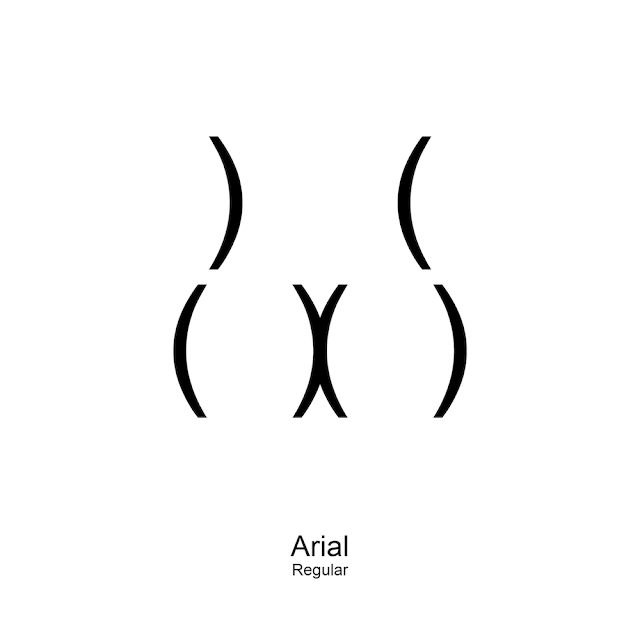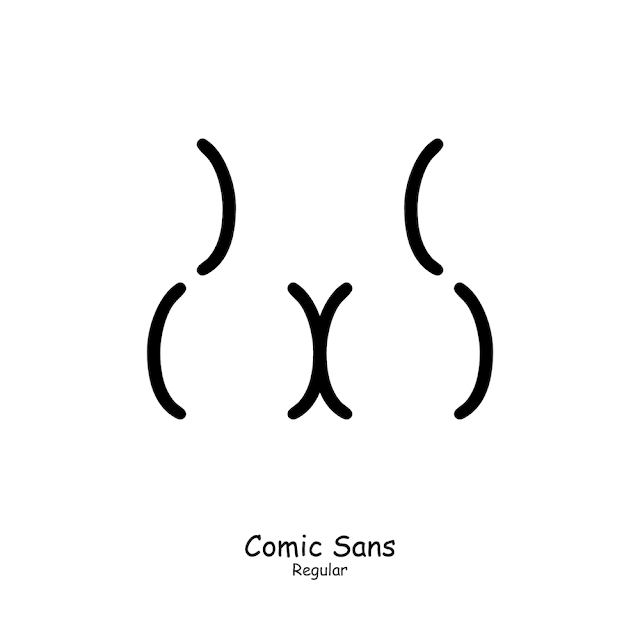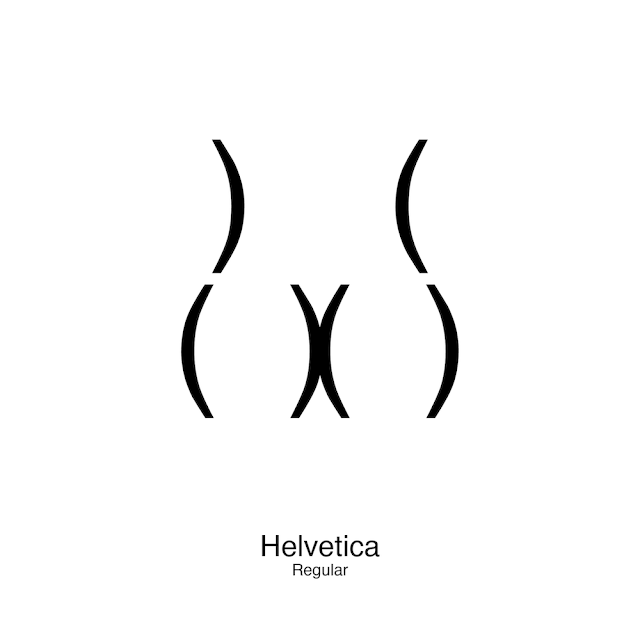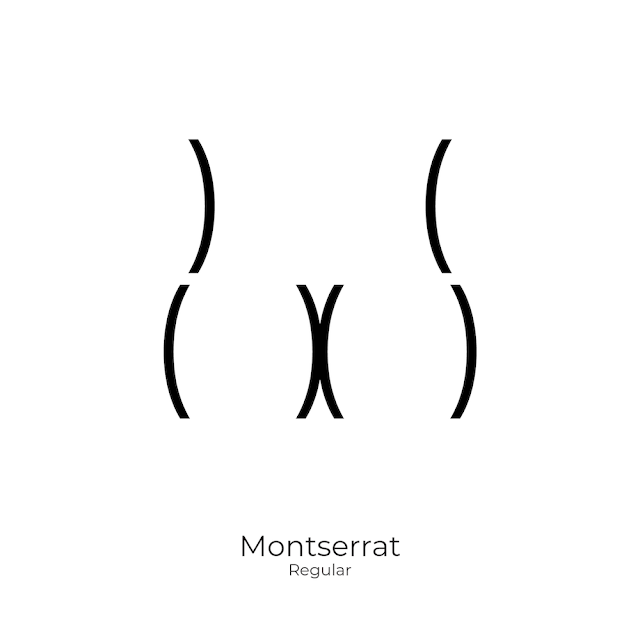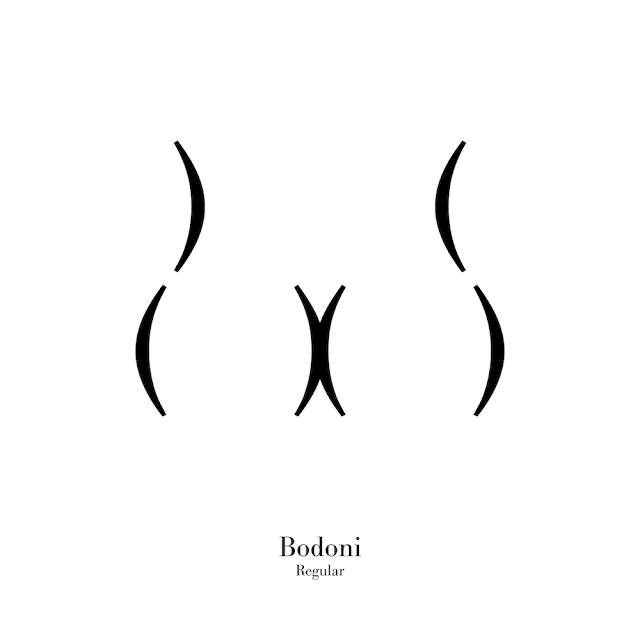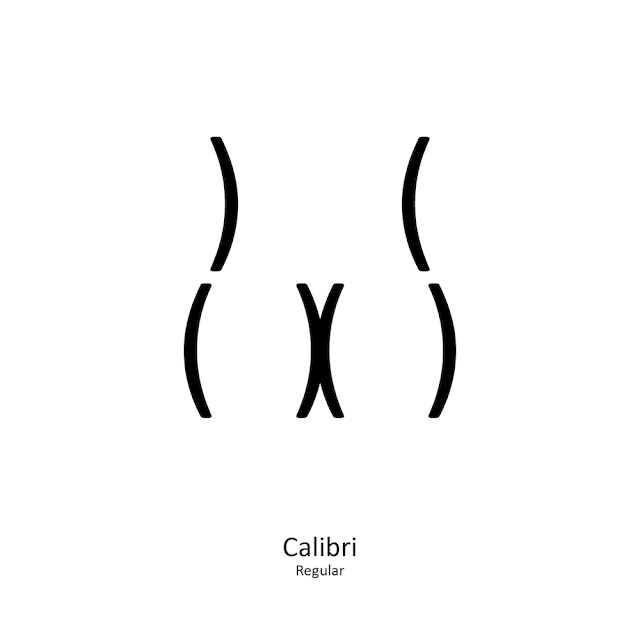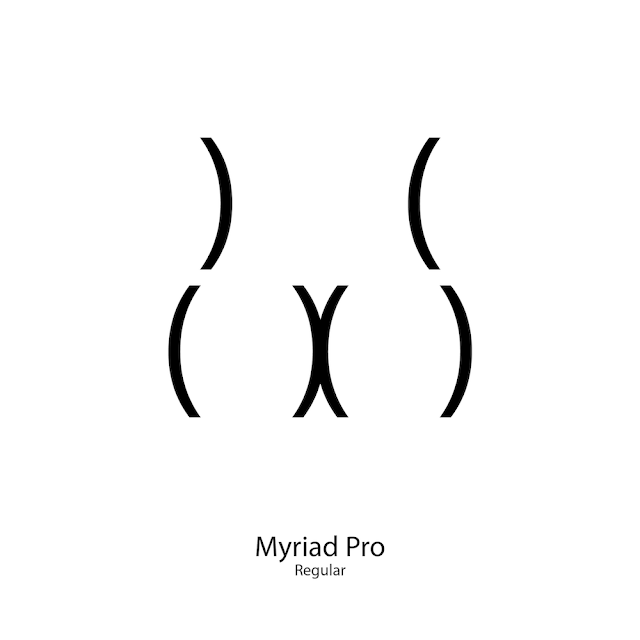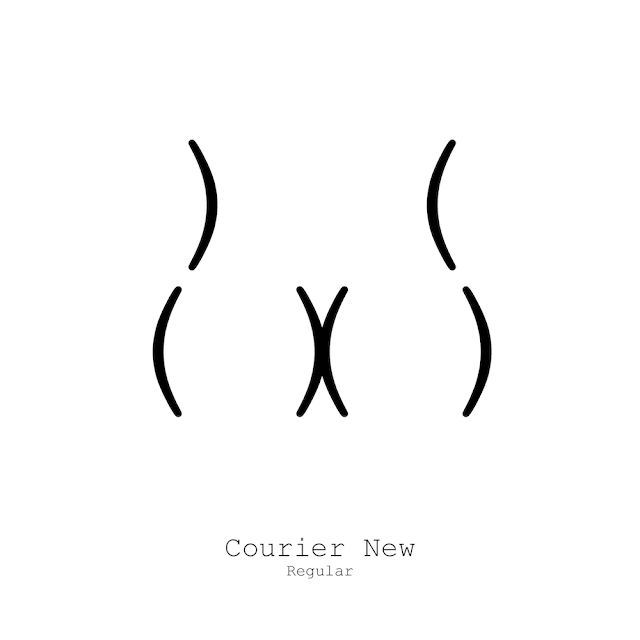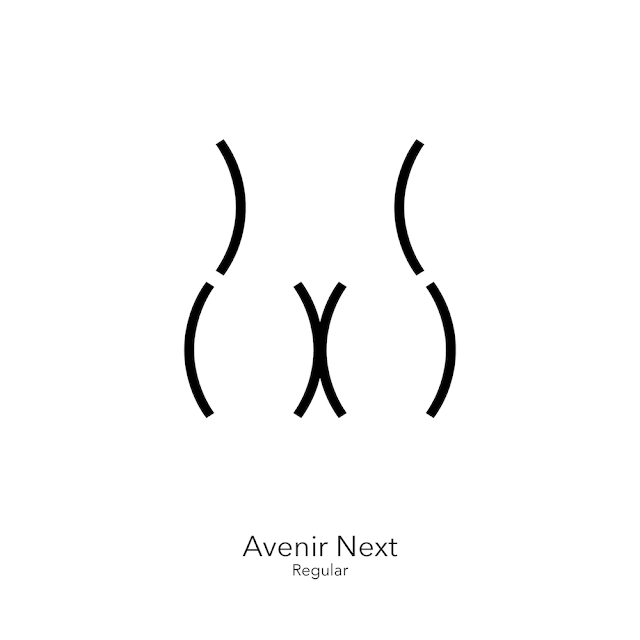
FontHub, el «portal» líder de la anatomía de la tipografía en el mundo
FontHub. La creación del diseñador Viktor Hertz combinó el erotismo con diferentes tipos de fuentes .
Viktor Hertz es un talentoso diseñador sueco de 36 años, que decidió unir la tipografía y el erotismo, apoyado en su experiencia como Director de Cine. Hertz siempre se ha inspirado en la cultura pop, la sátira y el humor, desde donde toma ideas fuertes para basar su trabajo creativo. Cabe resaltar que sus clientes incluyen marcas como Ray-Ban, Universal Music y, por supuesto, IKEA
Es así como nace “Fonthub”, una copia tipográfica del sitio web de videos para adultos, que pretende convertirse en la metáfora de lo que sería el sitio ideal para los amantes de los diferentes tipos de fuentes.
La intención de Hertz es regalarnos una colección de traseros de diferentes tipos, creados a partir de  tipografías icónicas en el mundo del Diseño, como Arial, Adobe Garamond Pro, Baskerville, Bodoni, Comic Sans, Calibrí, Myriad Pro, Helvética, Papyrus, Roboto, Montserrat, Zapfiro, por mencionar algunas.
Cabe destacar que este “sitio web” no es real sino solo es un proyecto, pero que creemos vale la pena compartir.